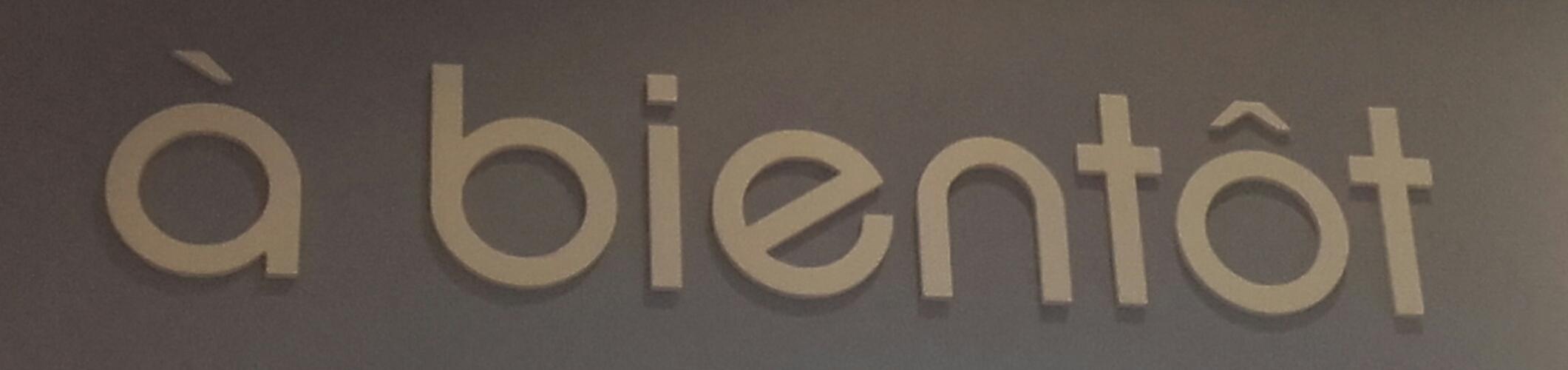
Geometrischer Supermarkt-Font
Welcher Font ist das?
Der sieht aus wie eine Kreuzung von Futura und Koch (die aber beide viel schöner sind).
Gestern gesehen in Frankreich.